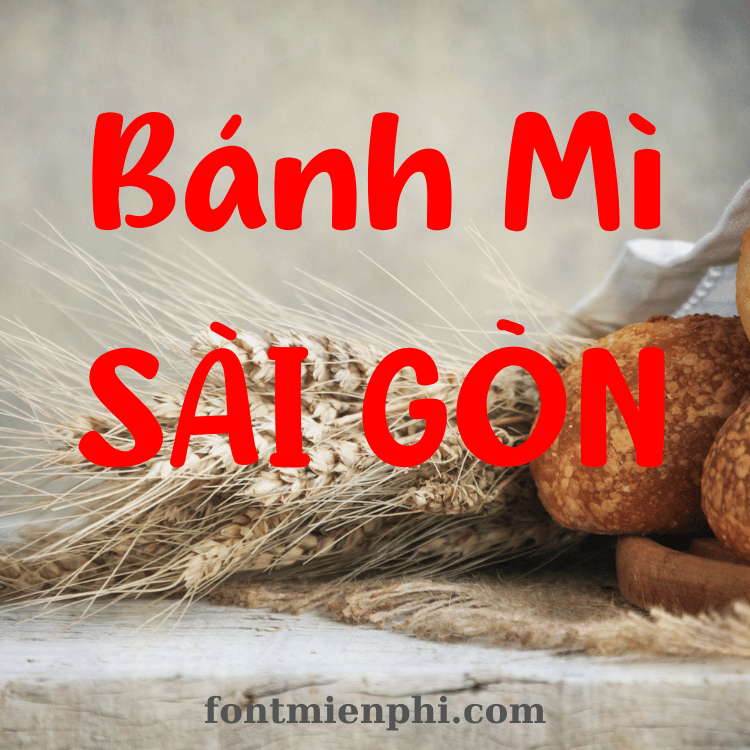
Font Việt hóa VIP Season Prime
Giới thiệu về Font Việt hóa VIP Season Prime
Trong thế giới thiết kế đồ họa hiện đại, việc lựa chọn một bộ Font Việt hóa VIP Season Prime chất lượng đóng vai trò then chốt giúp tác phẩm của bạn trở nên ấn tượng. Đây là bộ phông chữ được tinh chỉnh kỹ lưỡng về đường nét, mang phong cách thanh lịch và chuyên nghiệp, rất phù hợp cho các bạn học sinh, sinh viên làm báo cáo hoặc giáo viên thiết kế bài giảng sinh động. Khi tìm kiếm một Font Miễn Phí để làm mới giao diện bài thuyết trình, Season Prime luôn là lựa chọn hàng đầu nhờ khả năng hiển thị rõ nét và tính thẩm mỹ cao.
Ưu điểm nổi bật của bộ phông chữ
Đặc điểm khiến nhiều người yêu thích Font Việt hóa VIP Season Prime chính là sự kết hợp hài hòa giữa nét cổ điển và hơi hướng hiện đại. Bộ chữ này đã được tối ưu hóa hoàn toàn bảng mã tiếng Việt, giúp người dùng không còn lo lắng về lỗi hiển thị dấu khi gõ văn bản trên các phần mềm như Word, PowerPoint hay Photoshop. Điều này cực kỳ hữu ích trong môi trường học đường, giúp các em học sinh dễ dàng sáng tạo các mẫu thiệp, tờ rơi hay bìa sách đẹp mắt mà không tốn quá nhiều công sức chỉnh sửa kỹ thuật.
Cách ứng dụng Font Việt hóa VIP Season Prime hiệu quả
Để tận dụng tối đa vẻ đẹp của bộ chữ này, bạn nên kết hợp chúng trong các tiêu đề lớn hoặc các đoạn trích dẫn quan trọng để tạo điểm nhấn thị giác. Font Việt hóa VIP Season Prime đặc biệt tỏa sáng trên các phông nền sáng màu hoặc các thiết kế tối giản, giúp thông điệp truyền tải một cách nhẹ nhàng nhưng sâu sắc. Hy vọng rằng bộ công cụ này sẽ giúp ích cho cộng đồng giáo dục trong việc nâng cao chất lượng thẩm mỹ của các tài liệu học tập hằng ngày. Nếu bạn đang tìm kiếm nguồn tài liệu uy tín, hãy truy cập ngay Font Miễn Phí, Font Việt Hóa, Font Việt hóa VIP Season Prime để sở hữu trọn bộ sưu tập tuyệt vời này hoàn toàn miễn phí.